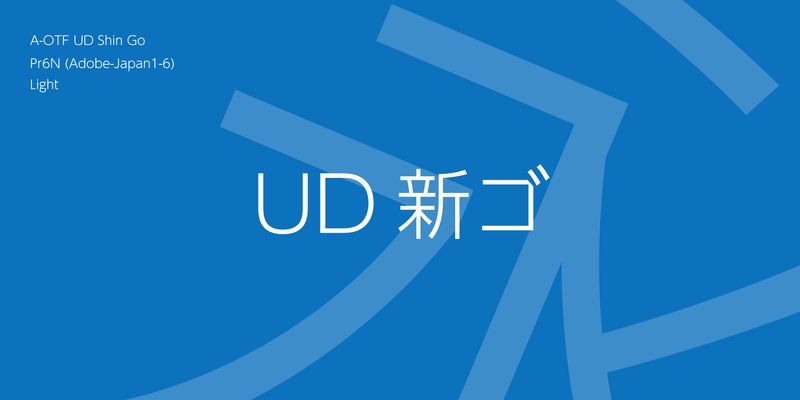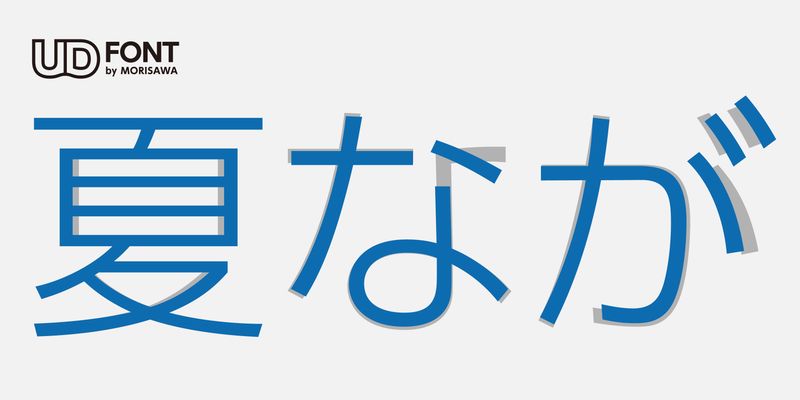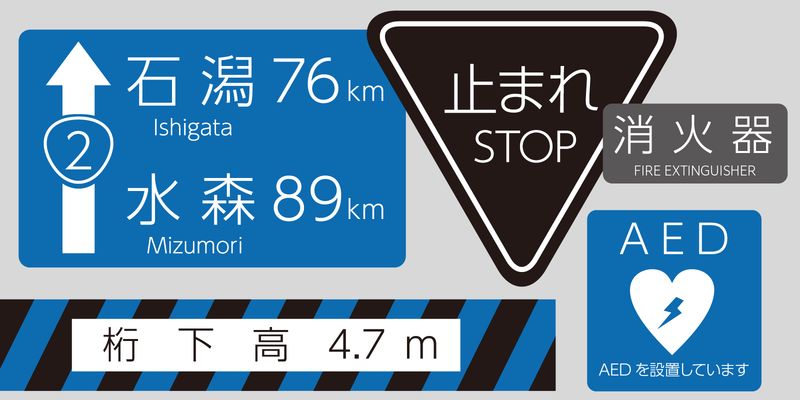
UD Shin Go는 가독성이 좋아 널리 사랑받는 Shin Go를 기반으로 한 보편적인 디자인의 산세리프 서체입니다. UD Shin Go의 서체도 가독성을 높이기 위해 최적화되었으며, 영숫자에는 가독성이 뛰어난 라틴 서체 ClearTone SG가 사용되었습니다. 이 타이프는 디스플레이 및 공공 간판과 같이 명확하고 잘 정돈된 디자인이 필요한 용도에 사용하기에 특히 적합합니다.